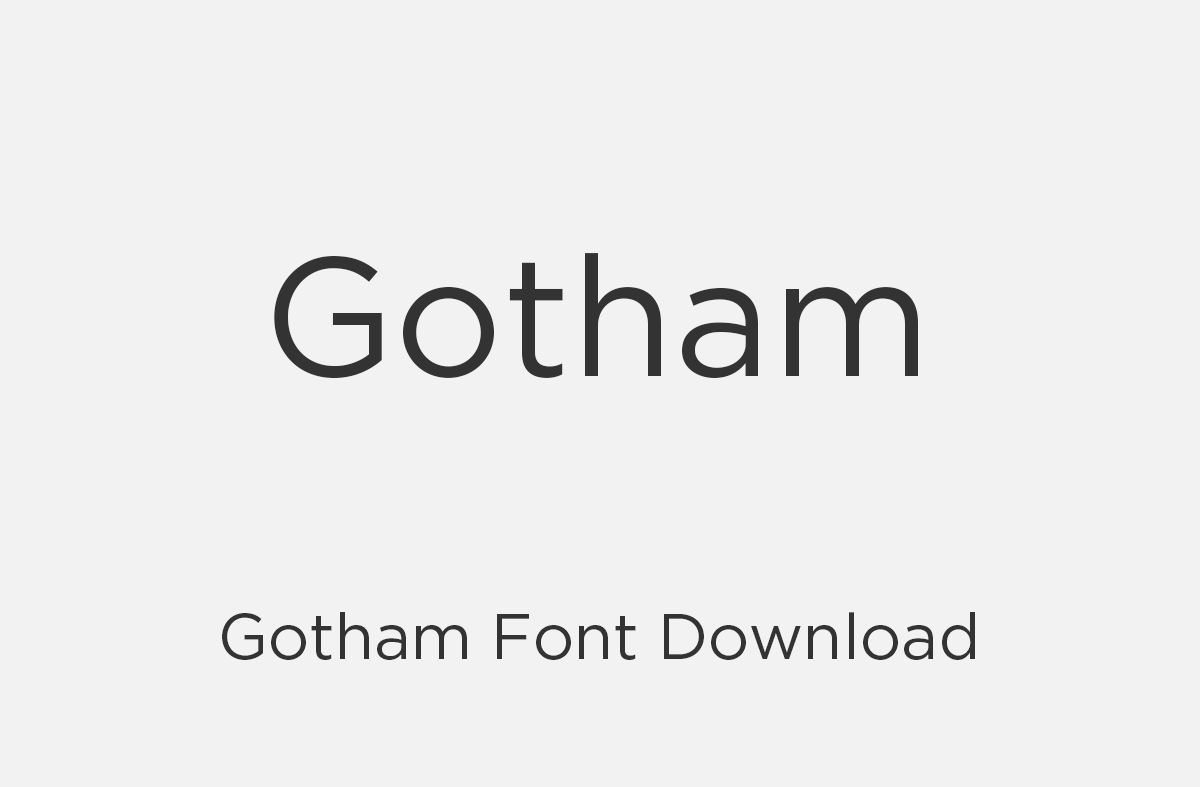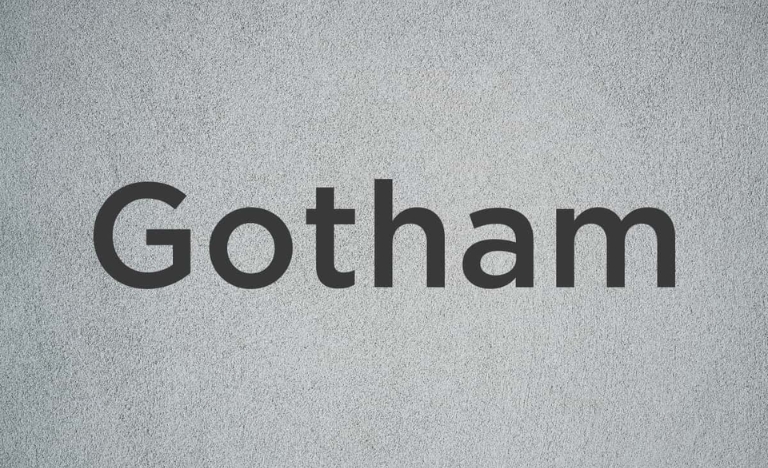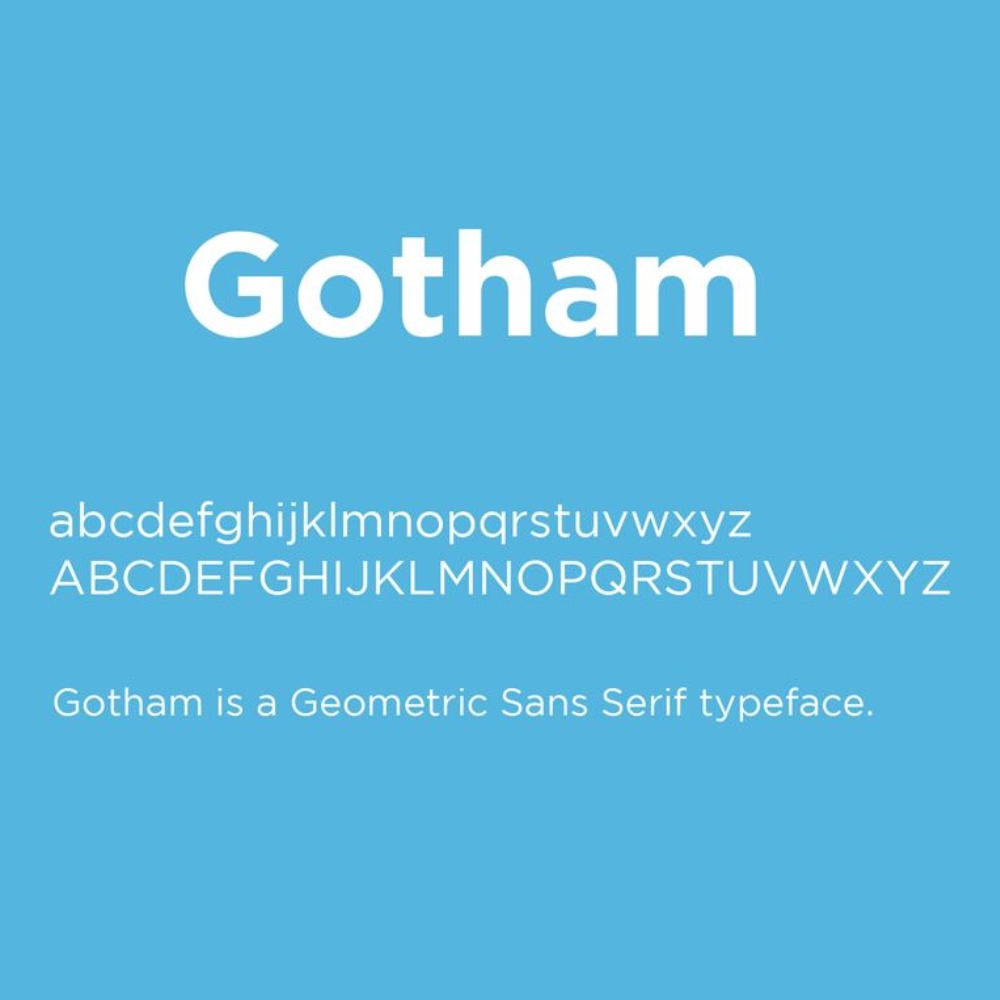
Download font Gotham là nhu cầu hàng đầu của các designer chuyên nghiệp khi cần một bộ phông chữ không chân (Sans-serif) mang phong cách đô thị hiện đại, vững chãi và cực kỳ sang trọng. Được thiết kế bởi Tobias Frere-Jones lấy cảm hứng từ các biển hiệu tại thành phố New York, Gotham đã trở thành biểu tượng của sự uy tín, từng được sử dụng trong các chiến dịch tranh cử tổng thống và bộ nhận diện của các tập đoàn tỷ đô. Doozypack.vn cung cấp link tải font Gotham Việt hóa trọn bộ, giúp bạn sở hữu phông chữ đẳng cấp để thiết kế bao bì mà không gặp lỗi dấu tiếng Việt.
Đặc điểm thiết kế vượt trội của bộ font Gotham
Gotham không chỉ là một phông chữ hiện đại thông thường; nó là kết quả của sự nghiên cứu về tỉ lệ hình học hoàn hảo để mang lại trải nghiệm thị giác mạnh mẽ nhất.
Phong cách Geometric Sans-serif hiện đại
Đặc trưng lớn nhất của gotham download font là cấu trúc chữ dựa trên các hình khối hình học cơ bản nhưng được tinh chỉnh để trông tự nhiên và dễ đọc. Các đường nét dứt khoát, độ mở của chữ rộng mang lại cảm giác minh bạch, trung tính và chuyên nghiệp. Chính vì vậy, Gotham là lựa chọn số một cho các thương hiệu muốn khẳng định vị thế dẫn đầu và sự bền vững.
Khả năng hiển thị ấn tượng ở mọi kích thước
Gotham sở hữu x-height (chiều cao chữ cái thường) lớn và khoảng cách chữ được tính toán khoa học. Điều này giúp mắt người nhận diện mặt chữ nhanh chóng từ khoảng cách xa trên các bảng hiệu hoặc ở kích thước cực nhỏ trên tem nhãn sản phẩm. Bản download font gotham việt hóa tại Doozypack.vn đảm bảo bộ dấu tiếng Việt được đặt cân đối, không phá vỡ nhịp điệu hình học vốn có của font gốc.
Hệ sinh thái Gotham Font Family đa dạng
Khi bạn thực hiện tải font gotham, bạn sẽ tiếp cận được dải biến thể phong phú, đáp ứng mọi bài toán về phân cấp thông tin (Typography Hierarchy) trên bao bì:
- Gotham Regular & Medium: Lựa chọn lý tưởng cho nội dung mô tả, bảng thành phần dinh dưỡng.
- Gotham Bold & Black: Gotham bold download font và gotham black free download font giúp tạo ra những tiêu đề mạnh mẽ, quyền lực và thu hút thị giác tuyệt đối.
- Gotham Rounded: Việc tải font gotham rounded là giải pháp tuyệt vời nếu bạn muốn thương hiệu trông hiện đại nhưng vẫn giữ được sự thân thiện, gần gũi nhờ các góc bo tròn tinh tế.
| Biến thể Font | Đặc điểm thị giác | Ứng dụng đề xuất tại Doozypack.vn |
| Gotham Regular | Cân đối, chuyên nghiệp | Dùng cho nội dung hướng dẫn sử dụng, địa chỉ sản xuất. |
| Gotham Bold | Vững chãi, nổi bật | Dùng làm tiêu đề chính, tên sản phẩm hoặc logo. |
| Gotham Rounded | Thân thiện, hiện đại | Thiết kế bao bì mỹ phẩm, thực phẩm sạch (Organic). |
Gợi ý lựa chọn: Nếu bạn thiết kế bao bì cho các dòng sản phẩm công nghệ hoặc startup, hãy sử dụng tải font gotham bold cho tên thương hiệu. Sự vững chắc của khối chữ Gotham sẽ tạo niềm tin rất lớn cho khách hàng ngay từ cái nhìn đầu tiên.
03 Ứng dụng của font Gotham trong sản xuất bao bì tại Doozypack.vn
Sự hiện đại và minh bạch của Gotham mang lại hiệu quả thị giác đặc biệt trên các ấn phẩm thực tế:
- Hộp cứng quà tặng doanh nghiệp: Tên công ty in bằng Gotham Bold kết hợp kỹ thuật ép kim mờ (Matte Gold) tạo nên vẻ ngoài vô cùng đẳng cấp.
- Túi giấy doanh nghiệp: Sử dụng Gotham cho địa chỉ và website giúp thông tin rõ ràng, chuyên nghiệp trên túi giấy Ivory cán màng mờ.
- Tem nhãn dán cao cấp: Cấu trúc rõ ràng của Gotham giúp các bảng thông số trên tem decal trở nên dễ tra cứu và thẩm mỹ hơn cho người tiêu dùng.